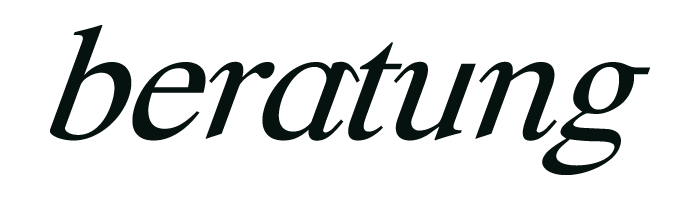
Schrift-»beratung«?
ich habe nur EPS-Dateien von dieser Schriftart zur Verfügung (von einer Visitenkarte), wobei der Text in Pfade umgewandelt ist. Es handelt sich um den Teil eines Logos (das ganze Logo möchte ich nicht zeigen, weil ich nicht gefragt habe, ob die Inhaberin damit einverstanden wäre). Es ist auch Fließtext in dieser Schriftart vorhanden, das heißt, es wurde nicht nur für das Logo an den Ankerpunkten herumgezuppelt. Besonders auffällig ist diese komische obere Serife beim a. WhatTheFont hat mir nicht weitergeholfen.
Ich finde die Schriftart nicht wirklich schick, daher würdet ihr mir sehr weiterhelfen, wenn ihr mir ähnliche Schriften nennen könntet, die eine solidere Wahl darstellen. Wurde hier an einem Schrift-Klassiker herumgeschnippelt?
Es handelt sich um den Teil eines Logos (das ganze Logo möchte ich nicht zeigen
Da du ja aber Alternativen suchst, gehört das in »Welche Schrift passt«, wo ich es jetzt hinschiebe und veröffentliche. Der Font ist übrigens die Happy Time, ein schrecklich verbastelte Times (New Roman).
Aber du hast schon recht, ich bin an der Schrift selbst nicht so sehr interessiert, sondern eher nach einer schöneren, soliden Alternative, die optisch nicht zu weit entfernt sein soll.
Und noch ein Tipp für dir Font-Suchmaschinen. Die haben nämlich gerade bei kursiven Schnitten oft Probleme, wenn sich die Buchstaben in der Senkrechten überlappen.
Hier hilft es oft, den Mustertext in einer Bildbearbeitung so zu bearbeiten, indem man jeden 2. Buchstaben herauslöscht, eventuell nachdem man den Text dupliziert hat, das man zuerst die Buchstaben 1, 3, 5… und dann die Buchstaben 2, 4 , 6… auf dem Bild mit reichlich Abstand hat.